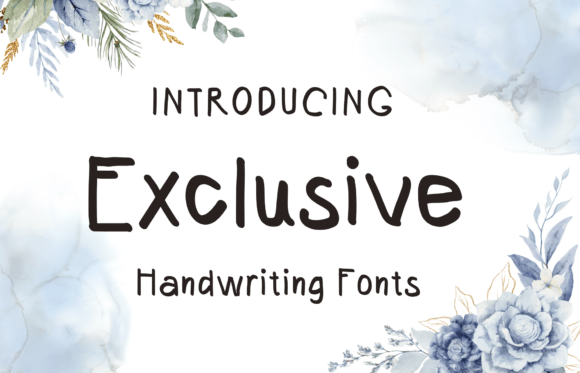
Exclusive
Mencari elemen desain yang tepat bisa jadi sulit, namun Exclusive menawarkan koleksi luar biasa yang akan langsung meningkatkan kualitas karya Anda.
Dibuat dengan presisi, Exclusive menyediakan vektor yang bersih, tipografi yang halus, serta lisensi komersial untuk ketenangan pikiran Anda.